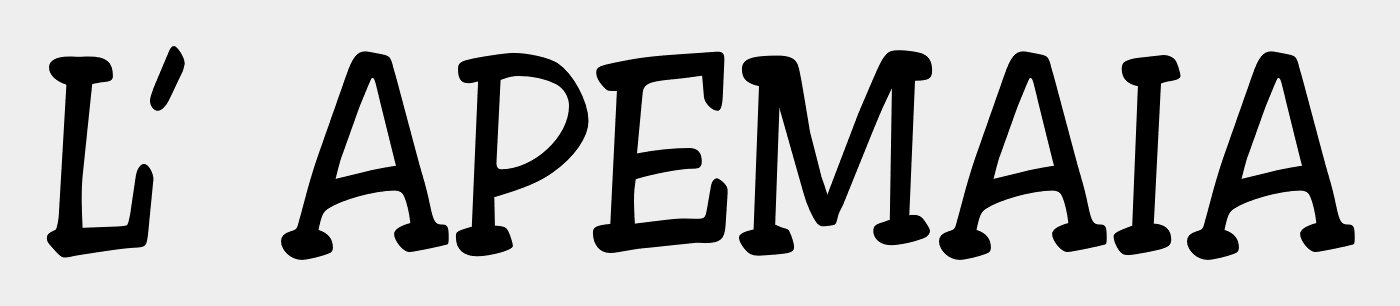
Suche Schrift von diesem Schriftzug eines Vorspanns (Die Biene Maja)
Bei der Englischen und Italienischen Version des deutsch-japanischen Animes "Die Biene Maja" aus dem Jahre 1975, werden beim Intro/Vorspann
eine andere Schriftart, als beim Deutschen Original verwendet.
Wer weis um welche Schriftart es sich handelt?
Entstehungszeitraum  -  1990-2000?
Synchronisationsstudios unbekannt
Fundort  -  Episoden der Serie "Die Biene Maja" (engl. Maya The Bee, ital. L'apeMaia);  YouTube Links zum selbst anschauen der Intros:
Ich kenne diese Schrift unter den Namen Jester.
Hier findet man etwas mehr Informationen:
Das hier ist der wichtige Abschnitt:
Digitizations of Filmotype Apache and August in varying quality can be found online under the names URW Apache, Cochise, Disney Print, Stanley, and Toledo. A version of these titled "Jester", seen on freeware font sites, works fine on screen but is very rough when blown up.